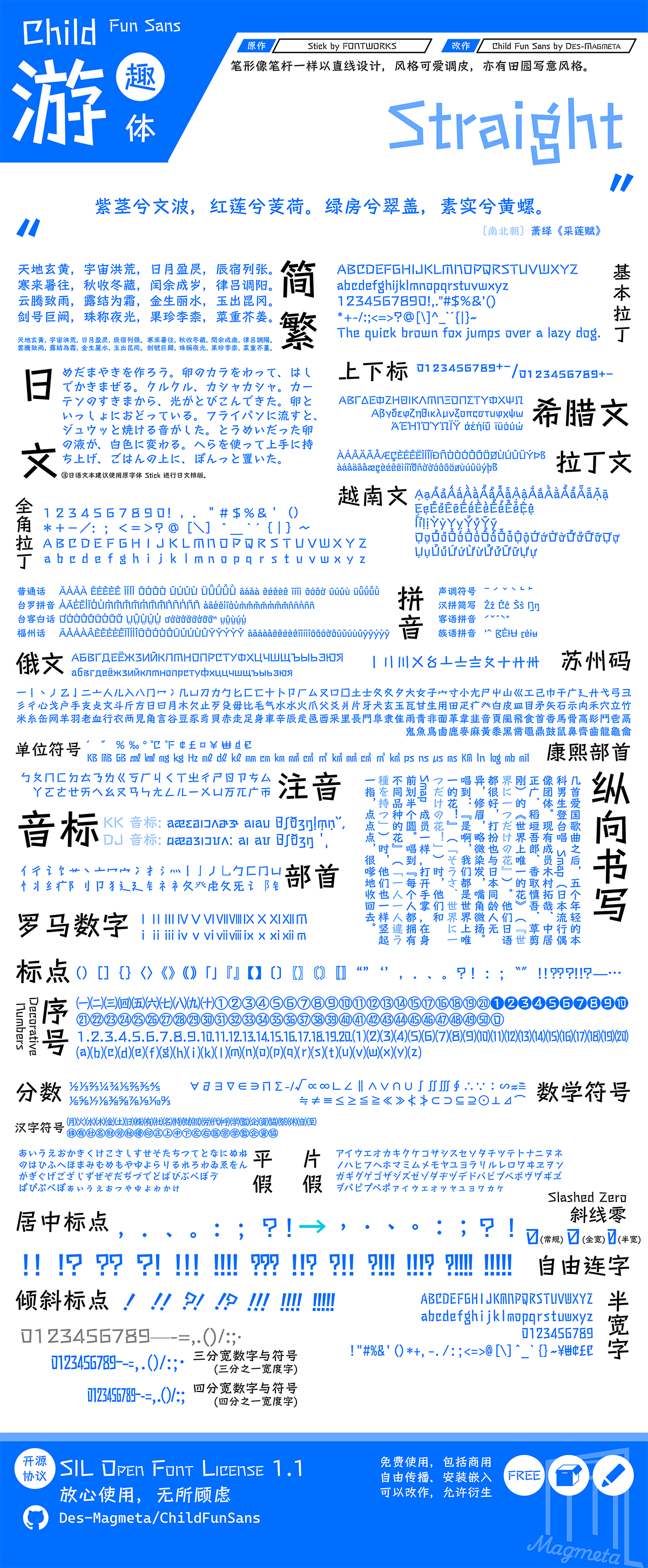
游趣体:基于Fontworks的Stick衍生 可爱调皮开源字体
游趣体因笔形像笔杆一样以直线设计,而被视为一款既可爱调皮,亦有田园写意风格的字体,本人基于 Fontworks 出品的日文字体ステッキ / Stick 扩充、调整字形,并编辑、适当增加 OpenType 特性,以满足简体中文的使用需求。
补字计划
简体部分
① 包括《义务教育语文课程常用字表》、GB/T 2312-1980、《现代汉语通用字表》《通用规范汉字表》。
② 部分字形差异视为设计特性,不做修改,如「厶」「幺」「亥」等字。
繁体部分
由于该字体目前定位仍以简体为主,目前无对原字体包含的繁体部分增补及修改的计划。
2. 在补齐 GB/T 2312-1980 前,此字体将出现一定的缺字可能。在不介意字体回退的情况下,如需支持缺字字符,请移步「游趣体融合」/ Child Fun Sans Fusion。
3. 自 0.300 版本起,「游趣体」支持 Unicode 变体序列(Unicode Variation Sequences, UVS),用于弯引号“‘’”宽度和全角标点符号,.、。:;!?位置的选择,支持变体序列的字符和所搭配的选择符详见「游趣体」变体序列一览表了解。经作者测试,WPS Office、PowerPoint (Microsoft 365) 软件不支持此特性,使用时需留意。
优化 100 汉字字形,无新增字符。
• 修复 bug:移除注音符号直排相关字形及其 OpenType,解决移动端行高过高、整体下沉问题。
• 新增汉语拼音 ng 简写「Ŋ」「ŋ」的四声标调组合字形;
• 修缮部分符号、汉字;
• 新增く字点「〳」「〴」「〵」字形,并通过 OpenType 特性自动调整为正确形态;
• 修改多数目标范围外的汉字写法,改为多数同 TC 版,以便后续跟进 TC 版更新。
• 修复「有限会社」「財団法人」等合字的高度异常问题;
• 参照「『霞鹜开源字体』外字初步整理一览表」、奈白不弍「《通规》外字整理」等字表,加入一部分外字;
• 修缮和新增部分字母和符号;
• 修复 「ЂU+0402」「ЋU+040B」错形问题,调整「ђU+0452」「ћU+045B」字形;
• 修正「㊞㊟㊣㊤㊥㊦㊧㊨」因 OT 类别错误导致字体渲染异常问题;
• 修改制表符「╭╮╯╰╱╲╳」U+2560~U+2573字形。
• 修复「姆」「渍」「瞪」轮廓异常问题;
• 修复「鿬」字形误作「钿」的问题,目标字汇内「楹」「爇」漏改问题;
• 更改 U+2550「═」、U+255E「╞」、U+2561「╡」、U+256A「╪」字形,为 1.0 版本加入制表符准备;
• 调整部分西文与符号风格不一致、比例不协调问题,调整部分汉字字形。
• 修复以往版本「轱U+8F71」字形错误显示为「⿰车占」的问题。
• 修复「丼U+4E3C」字形错误显示为「似U+4F3C」的问题;
• 修复「煲U+7172」字形错误显示为「㷛U+3DDB」的问题;
• 修复「煲U+7172」错形问题基础上,将原字形重映射到正确码位。
• 对字体名称作以下变更:
原始名称 Original name 新名称 New name
游趣体 简 Child Fun Sans ZHS 游趣体 简 Child Fun Sans CHS
• 修改「′U+2032」「″U+2033」「∓U+2213」的宽度,并将原有的全宽符号设为通过「全角字符」fwid特性调用,相关联的特性进行相应调整;
• 调整「标点挤压」chws、「半角替代」halt、「基本附属标记」mark等若干 OpenType 特性;
• 修复部分字符轮廓问题、「堍」「褟」字形错误问题、「繇」包含部件漏改问题;
• 重制「车」「东」「佥」部件相关汉字,并优化上一版本部分字形约 520 字;
• 补齐《通用规范汉字表》所收字符,大约 925 字;
• 参照「文津宋体」,新增部分注音符号和附标符号结合的组合形,并针对小型注音符号新增竖排特性。
简体版更新详情
• 将「≤U+2264」「≥U+2265」显示与「⩽U+2A7D」「⩾U+2A7E」同形;
• 调整「㊆U+3286」「苡U+82E1」字形;
• 进一步筛选字符,移除了部分不常用的西文字母与符号。
• 新增符号「♩」「♫」;
• 复用 Stick 原有字形,新增「𣽽」U+23F7D,字形作「⿰氵⿱𣏟⺝」,与「潸」U+6F78字形作区分;
• 补齐「现代汉语通用字表」所收字符;
• 调整简体范围内含「兼」部件、「旡」部件的汉字,以及少量汉字的轮廓。
• 重制了「漫画标点符号」ss02特性相关字形;
• 简体版调整破折号U+2014位置,使得在简体中文环境下与汉字居中对齐。
• 修复部分汉字的笔画缺失等问题;
• 调整自由连字字形,并补全了 Adobe-Manga1 收录的标点合字;
• 对照「字屿云游手书」等字体,增加部分西文字母及方言用注音符号;
• 新增部分西文符号、包含汉字的符号;
• 对部分 OpenType 特性及其相关字形进行调整;
• 调整符号「≈」「≌」为全角形态;
• 修复个别汉字的轮廓问题;
• 将「聚」「褒」「裹」恢复为 Stick 原版字形,简体版不做修改;
• 新增对部首「⺺」「⻣」「⻪」的映射;
• 新增 GB/T 2312 所收部分字符对应的规范汉字,如「锺」;
• 新增少许西文和大量符号;
• 新增和调整部分 OpenType 特性。
• 优化部分字形,共修改约 40 字;
• 新增部分西文和符号;
• 新增部分字符组合对自由连字和ss02「漫画标点符号」特性;
• 新增部分字符和「 ⃝」U+20DD的组合字形;
• 补全 GB/T 2312 包含汉字、《通用规范汉字表》二级字;